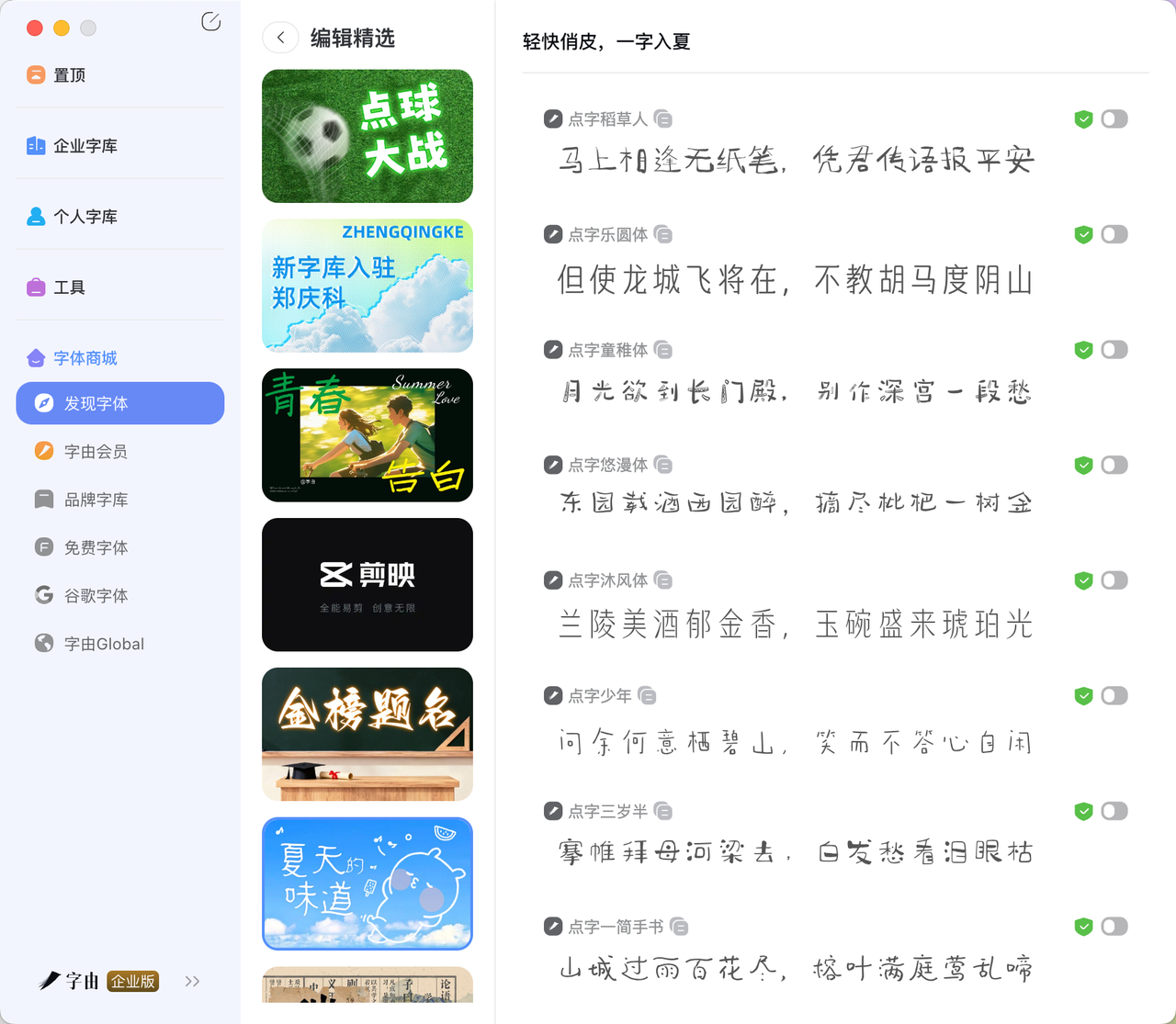
字体设计是生活美学
的重要拼图。特别是对于主打
VLOG
、
探店打卡
和
旅游
记录的创作者而言,
小红书配图
的精致排版,
视频封面字体
的抓人眼球,亦或是
户外活动攻略
中的
松弛
感营造,掌握这些
小众
且极具表现力的字体,都是提升
新媒体作图
与
视频剪辑
质量的关键。
本文将深度解析6款高
潮流
度的手写主题字体,助你轻松驾驭
Citywalk
、
露营
乃至
小城度假
的视觉表达。
字形结构疏朗,笔画纤细且带有一种随性的连笔感,整体视觉非常轻盈透气。这款字体自带一种“呼吸感”,极其适合用于
VLOG
片尾的字幕滚动,或者
生活美学
类的日常记录。在制作
周边游
或
旅游
随笔的
笔记封面设计
时,它能很好地中和画面的厚重感,传递出一种娓娓道来的叙事氛围,是
笔记种草
中营造
松弛
感的绝佳利器。
笔势奔放,连带自然,带有传统行草书的韵味,但结构又经过了现代化的简化,显得既古典又潮酷。极具视觉张力与情绪感染力。在
视频剪辑
中,它非常适合用作
旅游
高光时刻的
特效字体
,或者在
探店打卡
的
种草笔记
中作为大标题。如果你在分享
露营
体验或
户外活动攻略
,这款字体能瞬间点燃画面的激情,让你的
小红书配图
充满热血与
潮流
态度。
字形略扁,保留了手写的自然抖动,但笔画粗细相对均匀,带有一种理性的克制与少年的清爽。非常适合
年轻
群体的内容创作。在
Citywalk
路线推荐、
小城度假
的悠闲记录中,这款字体能精准传达出那种探索世界的纯粹与好奇。作为
视频封面字体
,它辨识度高且不显杂乱,是
新媒体作图
中保持
网感
的百搭选择。
笔触温润,字形偏长,带有一种毛笔书写的质感,但又不过于张扬,给人一种邻家般的亲切感。专为
生活美学
而生。无论是记录
探店打卡
时的细腻感受,还是分享
宝藏地点
的温馨贴士,这款字体都能完美融入。在
笔记种草
领域,它常用于正文排版或引言,能有效拉近与读者的距离,让
种草
文案更具说服力与温度。
笔意连绵,运笔如飞,字形开张,充满了动态的美感与一种洒脱不羁的江湖气息。如果你的
VLOG
或
旅游
内容主打“逃离城市”、“户外探险”或“公路旅行”,这款字体绝对是你的不二之选。它特别适合作为
户外活动攻略
的主标题,或者
旅游
纪录片的章节分隔字幕,将那种策马奔腾、
松弛
自在的氛围感拉满。
字形偏卡通,笔画圆润饱满,转折处处理得十分柔和,甚至带有一丝“幼态”的可爱感。这是
小红书配图
和
种草笔记
中的吸睛神器。在分享
探店打卡
的美食、
周边游
的亲子时光,或者是寻找
宝藏地点
的趣味攻略时,这款字体能迅速降低用户的阅读门槛,激发受众的好感度。它也是
视频剪辑
中用于强调福利或彩蛋的
视频封面字体
首选。
在实际的
新媒体作图
与
视频剪辑
工作中,不妨尝试将手写字体与胶片滤镜、拍立得边框或
Live
动图进行搭配。利用字体的温度去对抗数码图像的冰冷,能够让你的
笔记种草
内容更具人情味。同时,这些
小众
的手写字体也是制作
探店打卡
地图、
旅游
行程单等
免扣素材
时的最佳搭档。